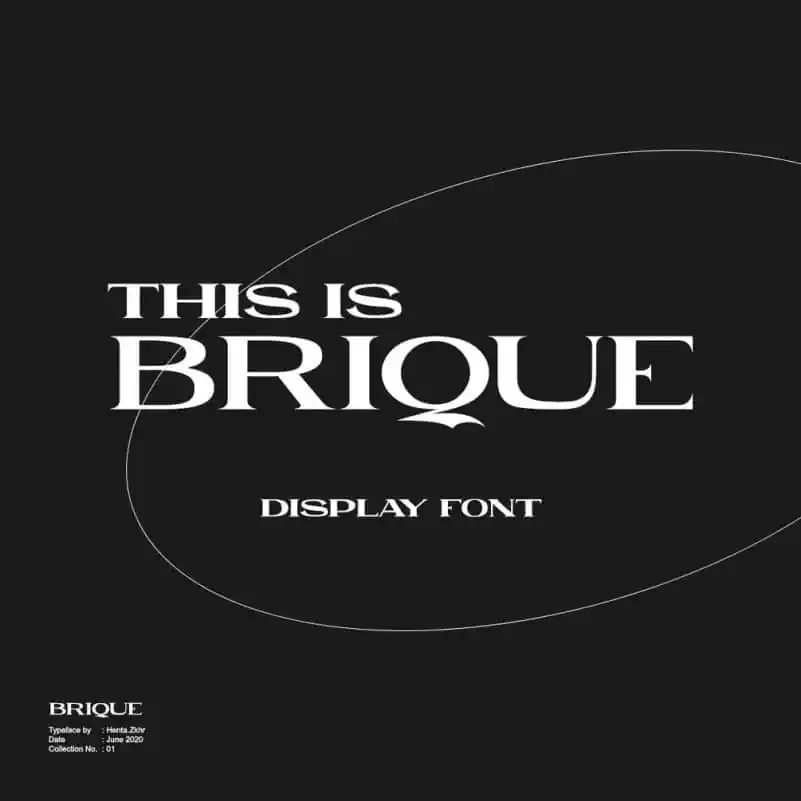
Brique Display Font – Download Grátis
A Brique Display Font é uma tipografia de exibição condensada que traz ao design um estilo único e poderoso. Inspirada na forma quadrada, essa fonte mantém sua consistência sem se tornar abafadamente rígida. Suas linhas fortes transmitem um forte significado, o que a torna perfeita para uso como texto de título ou subtítulo. Com seu elegante sêfor, ela surge como uma fonte bonita e ideal para exibição. A Brique é sem incluir caracteres minúsculos e alguns símbolos e pontuação. A Hamilton está trabalhando para atualizá-la o mais rápido possível. Este tipo de tipografia representa um equilíbrio entre ser eficaz em transmitir mensagens e elegante ao mesmo tempo, tornando-se uma opção popular tanto para designers quanto para aqueles que desejam dar um toque sofisticado a seus projetos visuais.